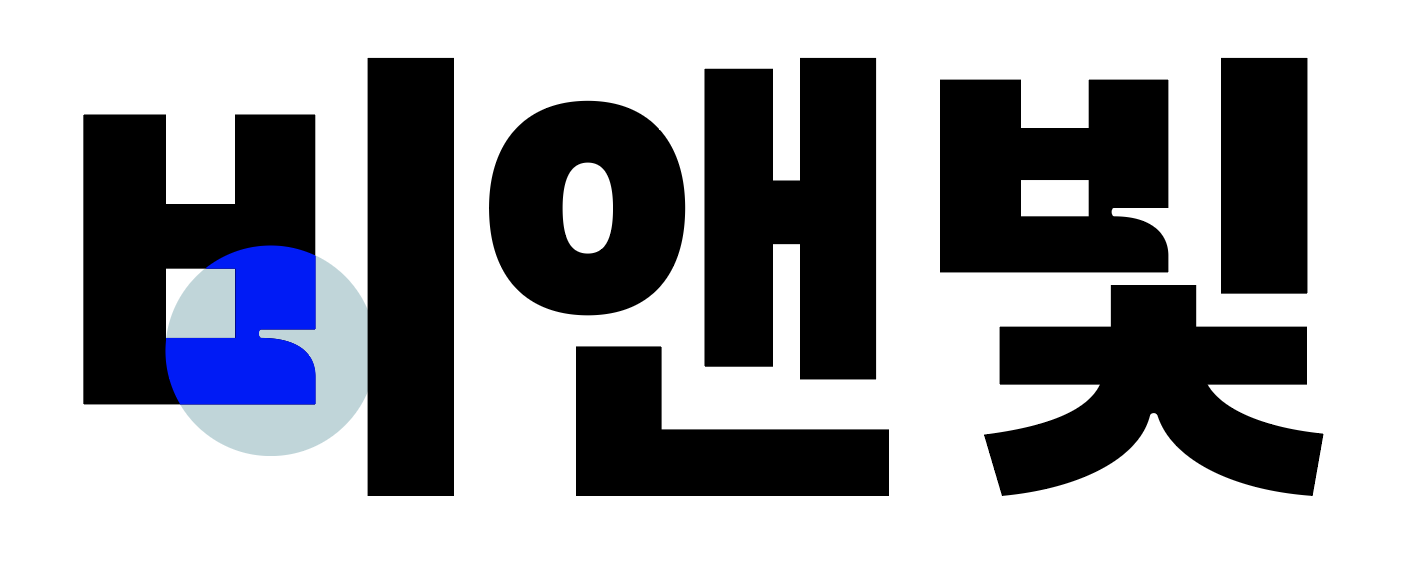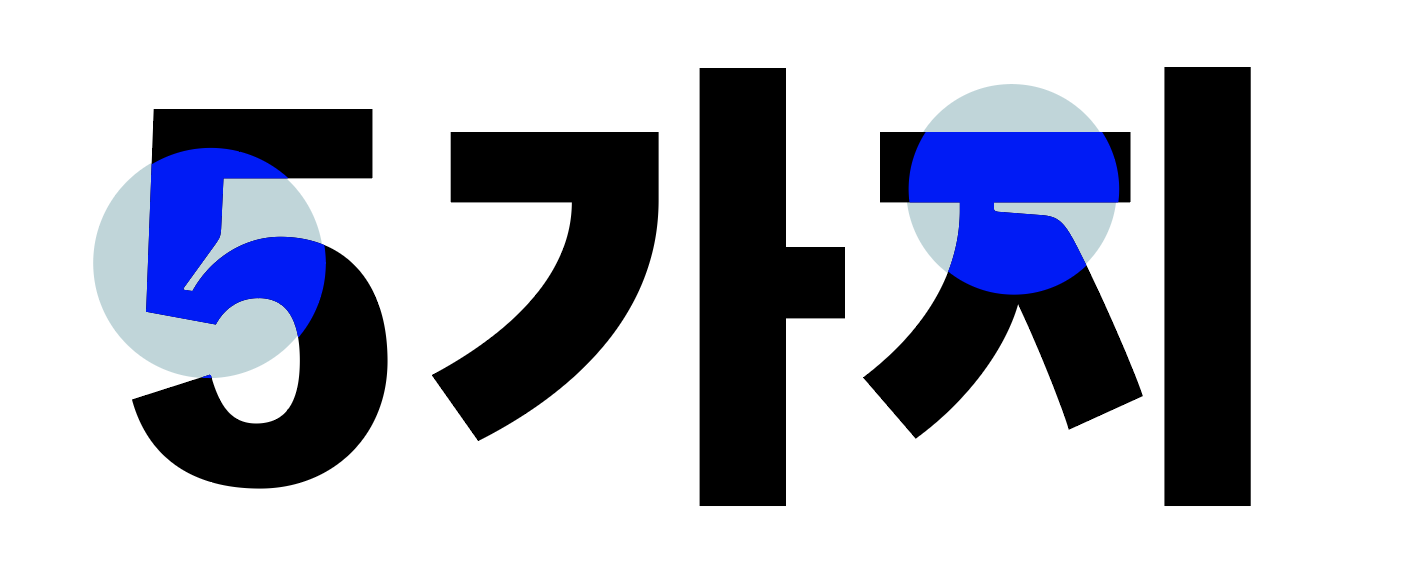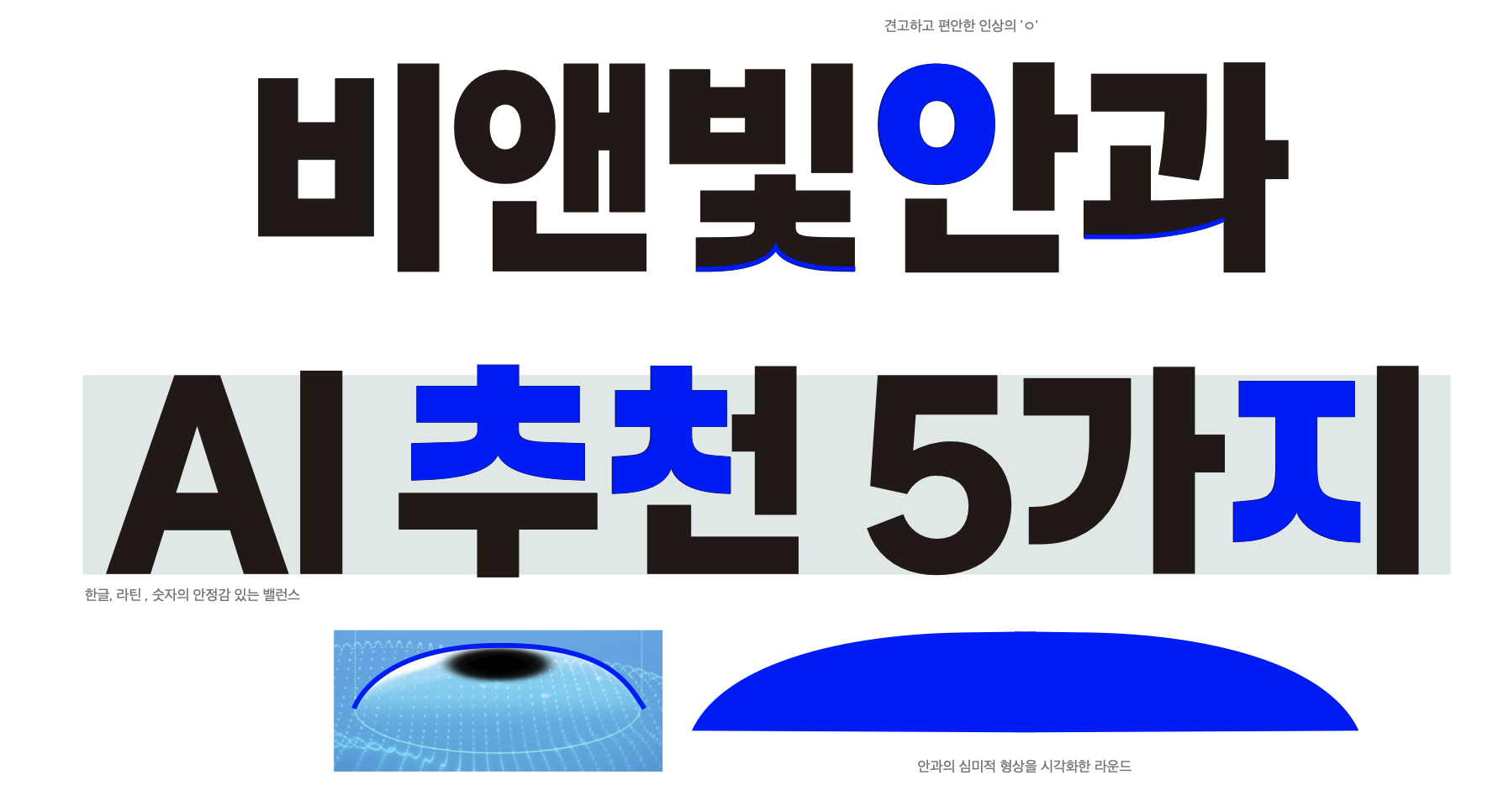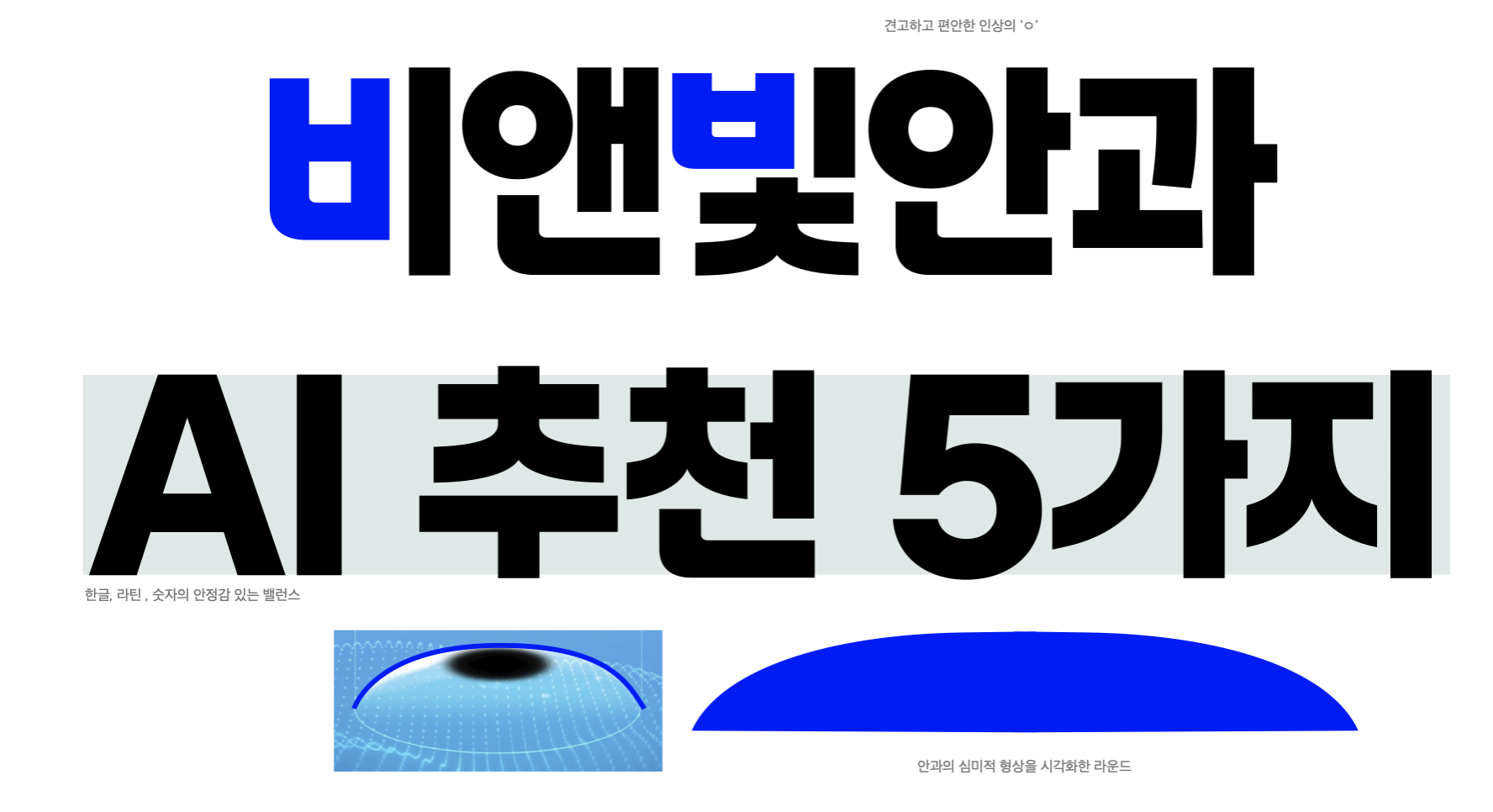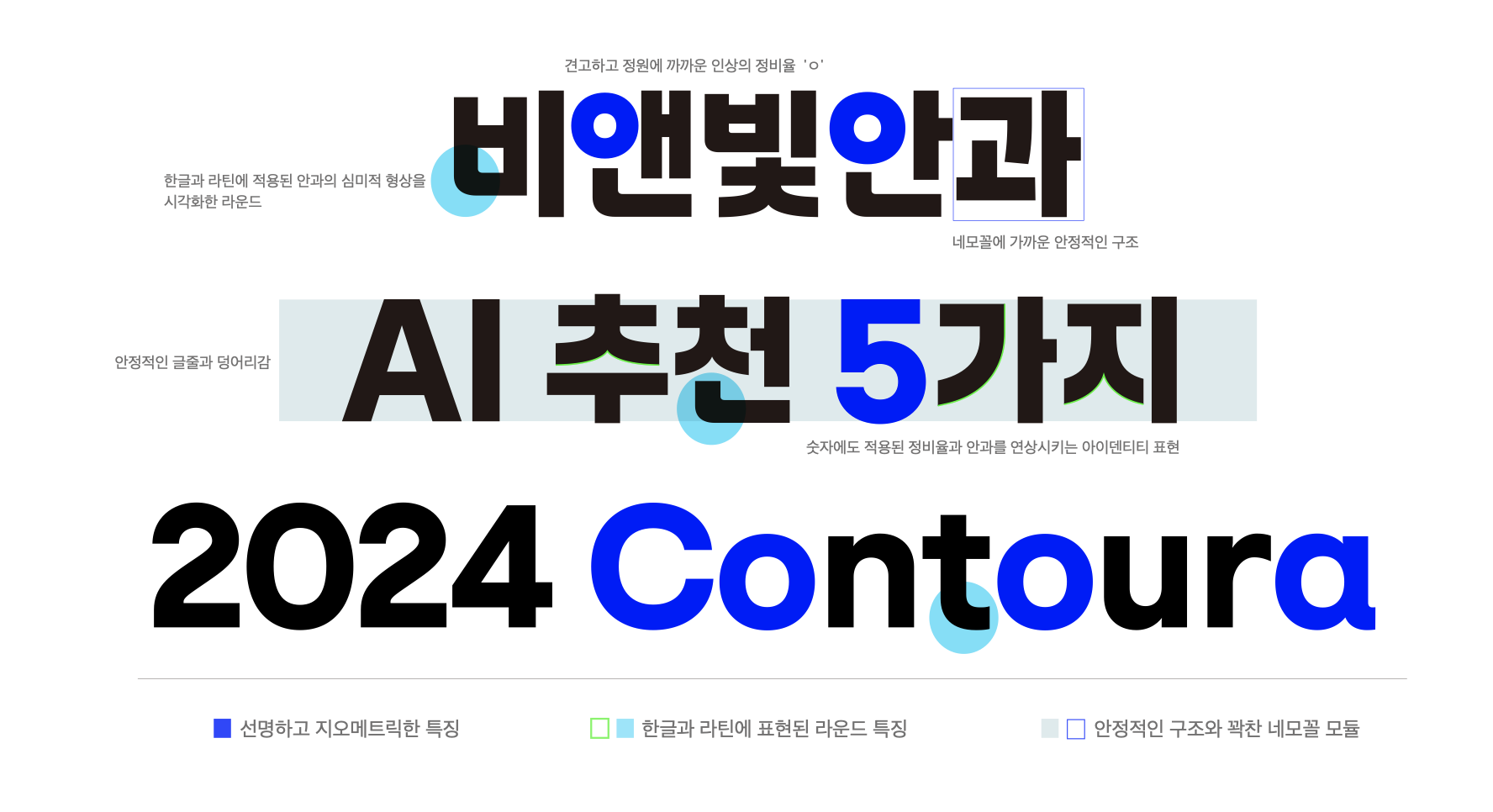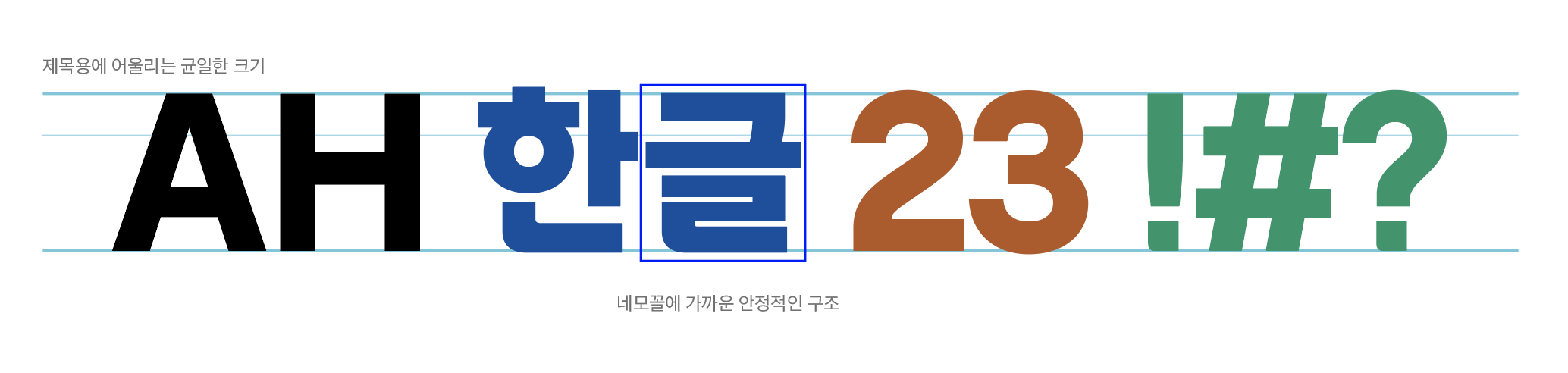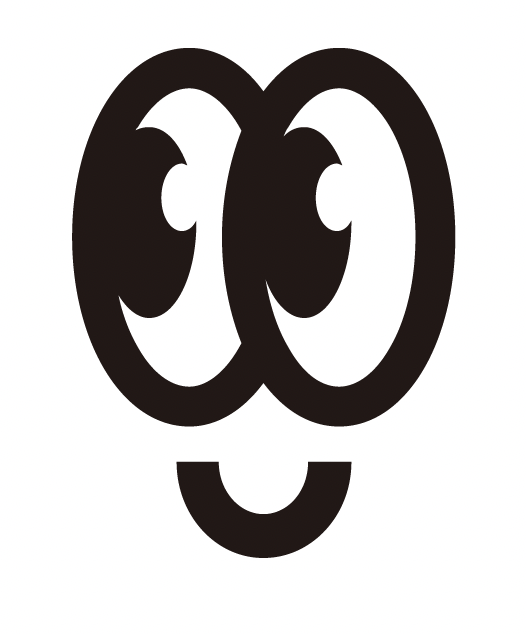
안과에서 폰트를?
비앤빛안과는 산돌과 함께 의료 업계 최초로 안과 전용폰트인 「비앤빛 라식체」 를 선보였어요. 비앤빛안과는 국내에 라섹 수술을 도입한 시력 교정 1세대 병원인데요. 업계를 선도해 온 비앤빛안과는 브랜드 아이덴티티(BI)를 강화하고, 브랜드 철학을 더 효과적으로 전달하기 위해서 폰트를 제작했어요. 제한적인 의료 광고의 틀에서 벗어나 고객에게 더 친근하고 일관된 목소리를 전함과 동시에 그동안의 사랑에 보답하고 고객의 일상에 더 가까이 다가가고자 「비앤빛 라식체」를 만들었어요.
브랜드 정체성을 찾는 과정 – 워크숍
산돌은 프로젝트를 본격적으로 시작하기 전 비앤빛안과 브랜딩의 접점에 있는 비앤빛안과 디자이너들과 함께 워크숍을 진행했어요. 클라이언트가 지향하는 핵심 가치를 파악하고 도출된 내용에 대해 깊이 있게 공감하기 위해서였어요.
고객이 비앤빛안과를 생각했을 때 떠오르는 추상적 언어를 시각화하는 과정에서 어떤 관점을 가지고 접근하냐에 따라 구체적인 형태에 미묘한 차이가 있을 수 있기 때문인데요. 같은 ‘동그라미’라도 어떤 지향점을 가지고 그리느냐에 따라 그 인상이 많이 달라질 수 있어요. 이런 미묘한 간극을 줄이고 클라이언트와의 씽크를 맞추는 것이 워크숍의 목표였습니다. 비앤빛안과가 원하는 모습과 피하고픈 모습 등 지향점을 이야기하고 시중에 나와 있는 다양한 레퍼런스를 통해 간극을 좁혔어요.
워크숍에서 “병원 업의 근간이 되는 신뢰를 바탕으로 한 트렌디함의 탐구”라는 인사이트가 도출됐어요. 이에 따라 기본적으로 안정적인 구조에 친근, 정직한 표현으로 신뢰감을 구현하려 했어요. 그리고 업계를 선도하는 트렌디함과 20대 타겟을 위한 너무 가볍지도 무겁지도 않은 부드러운 친근함의 밸런스를 찾아가는 고민을 했어요.
비앤빛안과의 Hope & Fear_Workshop
시각적 아이덴티티 정리 – 프로토타입 개발
프로젝트를 이끌어갈 인사이트 도출에 이어 프로토타입 개발도 산돌과 비앤빛안과가 함께했어요. 첫 프로토타입은 시력 교정술을 실행하는 안과의 정밀함으로 접근했어요. 아래의 자료는 안정적이고 견고한 형태를 바탕으로, 안과가 가진 특성과 기술력을 강조하는 ‘정밀함’을 시각화했던 시안입니다.
레이저의 정밀함을 시각적으로 표현한 요소들
이런 접근을 한 이유는 다른 진료 과목과는 다르게 우리의 눈을 다루는 안과에서 ‘초정밀함’은 매우 중요하다고 느껴졌기 때문이에요. 시력 교정술은 레이저가 각막 표면을 마이크론 단위로 조율하는 수술인 만큼 1마이크론의 차이도 큰 차이점으로 다가올 수 있어요. 이러한 마이크론 단위의 “초정밀”을 시각적으로 풀면서 업계를 선도하는 첨단과 트렌디함을 담아 포인트를 구성했던 거죠.
비록 글자 안을 파고드는 표현이 비앤빛안과에서 추구하는 정직함과는 맞지 않아 바로 정 궤도를 찾긴 했지만, 이런 케이스처럼 프로토타입에서는 스펙트럼을 넓혀서 탐색하기도 해요. 이렇게 프로토타입 차수를 진행하면서 점점 그 범위를 좁히는 프로세스를 거치게 됩니다.
선택되는 것은 그것대로, 아닌 것은 아닌 대로의 큰 의미가 있어요. 비록 선택되지 않았지만 덕분에 나아갈 방향이 더 선명해졌어요. 최종적으로 비앤빛안과가 추구하는 견고함을 표현한 안정적인 구조와 안구와 각막의 곡률을 시각화한 시안이 선택되어 디벨롭을 시작했어요.
1차_안구와 각막의 곡률을 시각화한 시안
2차_지오메트릭한 형태와 친근한 라운드의 적용 시안
좁혀진 시안에서 좀 더 정직하고 지오메트릭한 형태를 더하며 친근한 라운드의 적용으로 정리해 나갔어요. 이 과정을 통해 도출한 정비율의 선명함과 트렌디함, 안구와 각막의 곡률을 모티브로 한 라운드 특징은 비앤빛안과의 신뢰감 있고 따듯한 감성을 담아내게 되었어요.
「비앤빛 라식체」 의 디자인 특징
「비앤빛 라식체」 는 단순한 브랜드 폰트가 아니라, 비앤빛안과의 철학과 가치를 담은 폰트예요. 그렇다면, 이 폰트가 가진 가장 큰 특징은 무엇일까요?
「비앤빛 라식체」의 특징
1. 선명하고 지오메트릭한 구조
2. 시력 검사표(란돌트 링)에서 착안한 디자인 요소
시력 검사에서 사용되는 ‘란돌트 링’의 구조를 참고하여, 수직/수평 구조를 명확하게 표현했어요.
이를 통해, 비앤빛안과의 ‘선명한 시생활을 돕는 병원’이라는 의미도 폰트에도 반영했어요.
란돌트링 (이미지 출처: 시력 검사 도식화_한국표준과학연구원)
3. 각막과 안구에서 영감을 얻은 부드러운 라운드 형태
4. 꽉 찬 네모꼴의 제목용 폰트
제목용 폰트로 사용될 수 있도록, 글자의 공간을 꽉 채워 무게감을 살렸어요.
광고, 홍보물 등에서도 가독성이 뛰어나도록 설계되었어요.
마치며 – 본문용 폰트 개발 중!
「비앤빛 라식체」 프로젝트를 하면서 산돌과 비앤빛안과의 지향점과 하는 일이 무척이나 닮아 있다고 느꼈어요. (우린 같은 곳을 바라봐..) 산돌은 누구나 자유롭게 표현할 수 있는 세상에 가치를 두고 쉽고 명료한 서비스로 다양한 고객을 만나고 있어요. 비앤빛안과가 시력 교정술로 선명한 시야를 제공하고 더 나은 삶을 선사하듯, 산돌이 개발한 폰트는 텍스트의 가독성을 높여 메시지가 선명하고 명확하게 전달되는데 그 지향점을 가지고 있기 때문이에요.
이렇게 작년 12월 비앤빛안과의 전용폰트, 「비앤빛 라식체」를 제작 완료했어요. 현재는 좀 더 진중한 목소리와 인상을 표현할 수 있도록 본문용 폰트를 개발하고 있어요. 개발 중인 본문용 폰트는 제목용 폰트인 「비앤빛 라식체」의 DNA를 최소한으로 유지하면서 라운드한 형태를 특징을 가지고 있어요. 또한 본문용이라는 기능에 충실하게 안정적이고 높은 가독성을 가진 구조로 제작되고 있어요. 「비앤빛 라식체」와 페어를 이룰 본문용 폰트도 곧 출시되니 많이 기대해 주세요!!
「비앤빛 라식체」에 숨어있는 딩벳
한글 2,780자 외의 글자를 치면
이런 얼굴이 나옴 >ㅁ<)